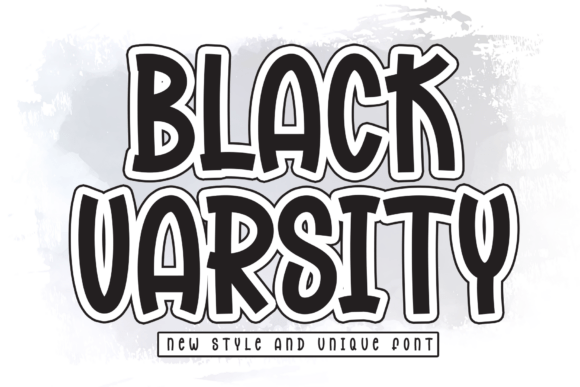
Black Varsity
Jika anda sedang mencari aset berkualiti tinggi seperti Black Varsity, pakej premium ini merupakan pilihan yang hebat untuk projek kreatif anda.
Sama ada anda mencipta produk POD (Print on Demand), jemputan perkahwinan atau grafik media sosial, Black Varsity amat bersesuaian.